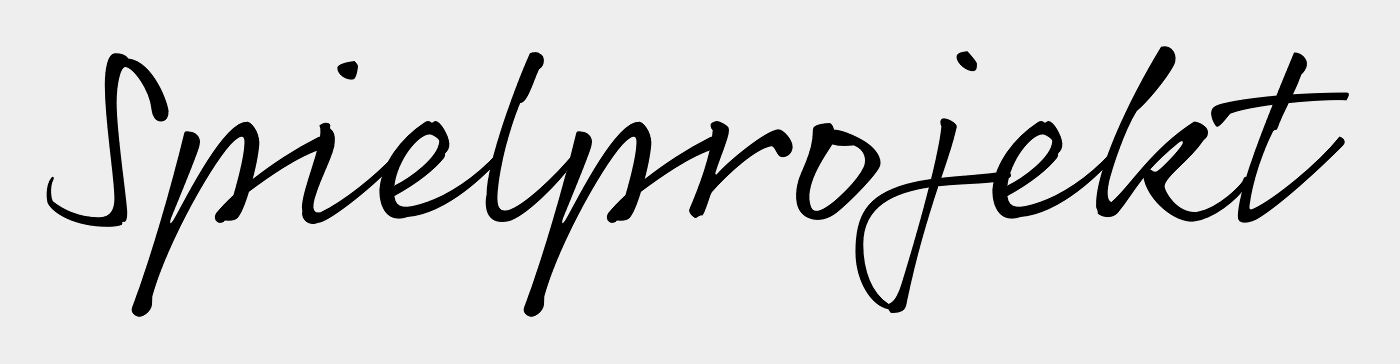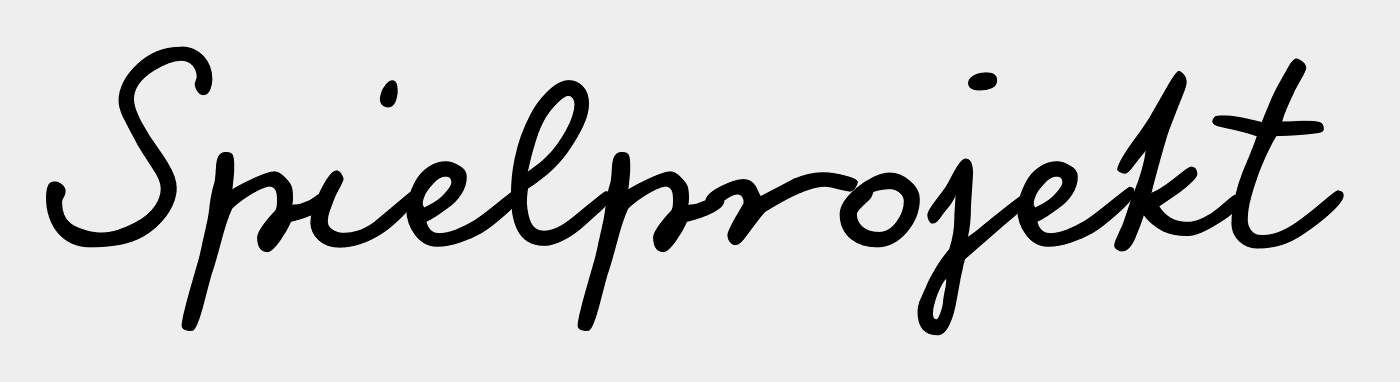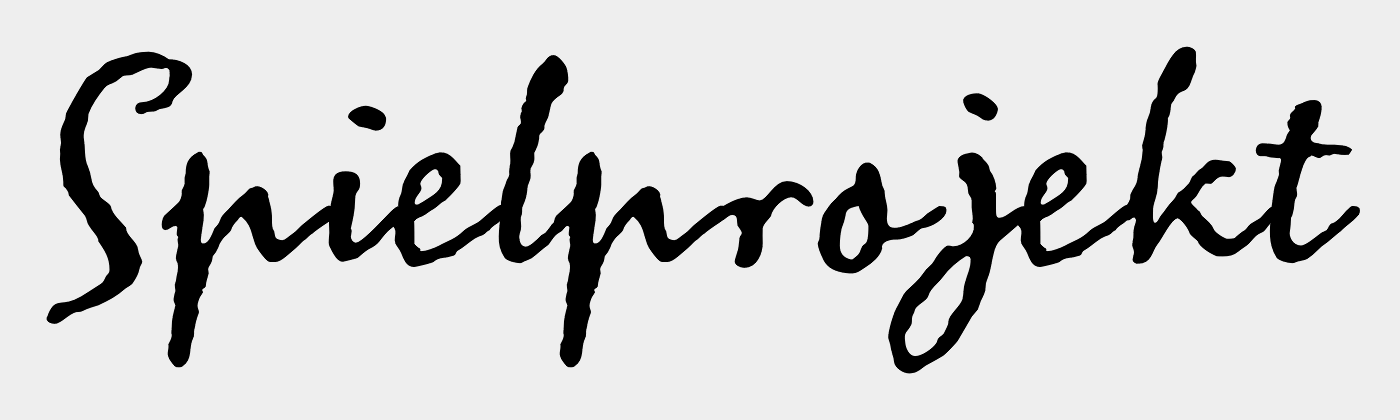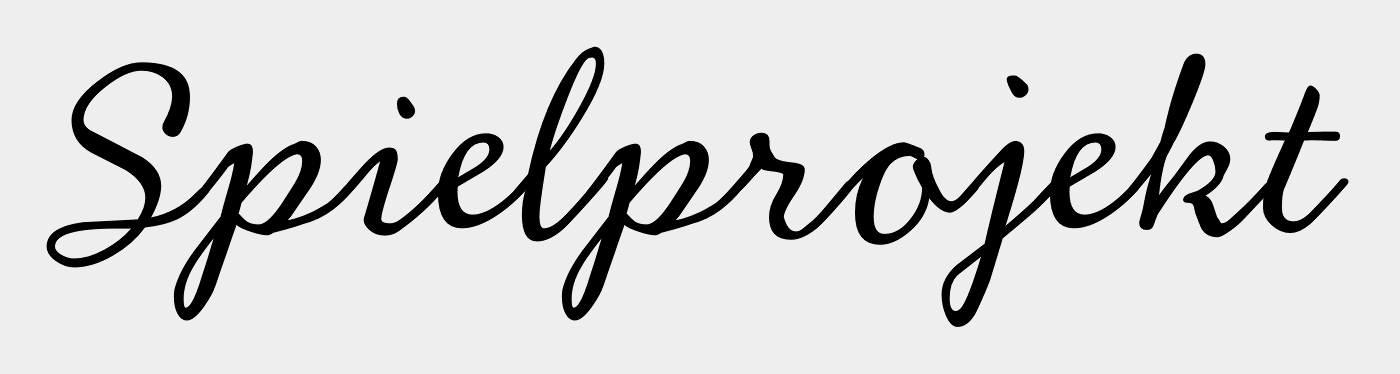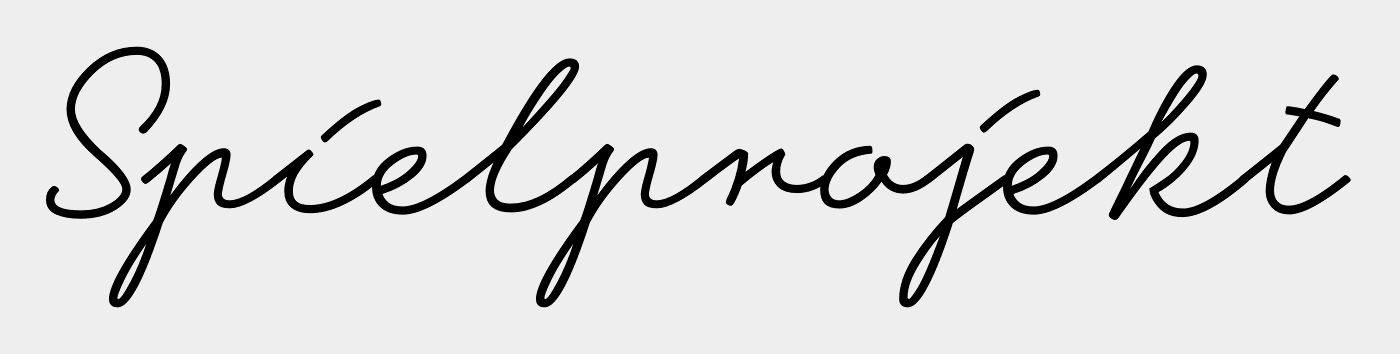
Alt aber modern – deutsch, aber nicht zu deutsch ...
Ich habe hier ein Projekt, wo ich die Charcuterie von der sehr geschätzten Laura W. im Logo eingesetzt habe – genauer gesagt die
Für ein Buchprojekt wollte ich jetzt passender Weise die
verwenden, da beide ja als Zusammenspiel entwickelt wurden. Soweit, so gut sieht das auch schön aus, wenn da nicht diese deutlich amerikanischen Versalien drin wären:
Bei dem Buchprojekt geht es um alte Kinderspiele, die von Senioren an Schulkinder weitergegeben werden und diese das dann künstlerisch aufarbeiten. In dem Buch werden die Spiele erklärt und die Bilder der Kinder gezeigt. Insgesamt geht es bei dem Projekt um diesen Austausch zwischen den Generationen. Deswegen hätte ich gerne eine Schrift die das auch widerspiegelt: irgendwie alt (30er/40er- evtl. 50er-Jahre) aber nicht plump altbacken sondern irgendwie auch frisch ... :-?
Was habe ich mir schon angeguckt?
Zierfische (gibt’s die noch irgendwo?), Movie Script etc. – zu schildermalerisch, sollte eher handschriftlich sein
Liebe ... – zu statisch und streng
Einen Folder habe ich mit der Charcuterie Cursive schon gemacht und die Idee der Schriftverwandschaft gefällt dem Kunden auch, aber ein paar Versalien finde ich dann doch sehr befremdlich. Wenn aber nichts anderes passendes in die Quere kommt werde ich die wohl in Kauf nehmen.
Ach so: Textschrift ist die Aller
Doch, doch – Script ist schon ganz richtig :nicken:
Mrs. White ist in der Tat etwas zu statisch, aber die Ropsen Script passt schon ganz gut, vor Allem in der Fetten :-P:nicken::gimmifive:
Vielleicht ist sie aber auch ein μ zu wild ... irgendwie dazwischen:-?
Die Sacre Bleu finde ich ja auch chic - aber dann hat sie leider ein z mit Unterlänge (seufz). Was ich schon an Schreibschriften mit "normalen" Buchstabenformen gesucht (und nicht gefunden) habe ...
Favoriten sind bei  mir jetzt die FF Ropsen und Goodlife Script – vor allem letztere ist der Charcuterie Cursive sehr ähnlich und hat schöne, viele Alternativzeichen :biglove:
Joe war auch ein guter Tipp :nicken: Kannte ich noch nicht :-o